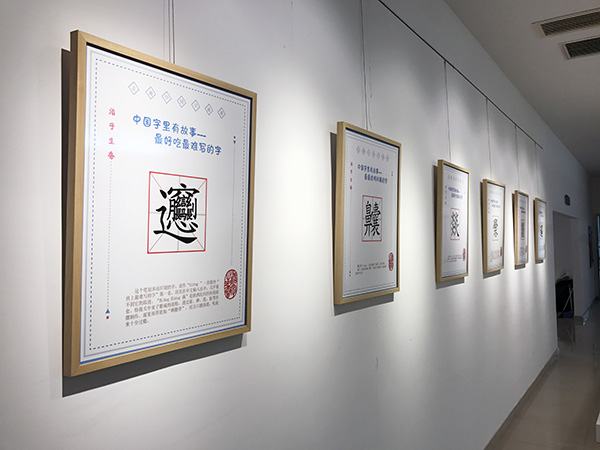
宋体、黑体、楷体等字体如何诞生?看“活字”的前世今生
从远古结绳记事到创世神话中的仓颉造字,至今我们仍然在使用汉字。千年传承让汉字这一神奇的方块字既古老又年轻。从北宋毕昇发明的泥活字,到如今通过电脑实现激光照排技术,黑、宋、仿、楷等字体“告别铅与火、迎来光与电”,成为如今的民族文化遗产。
“活字生香”展现场
澎湃新闻记者从发布会上获悉,“活字生香”活字文化艺术全国巡展将于24日在上海中华印刷博物馆开幕。展览将以“活字”为主题,通过解读活字艺术背后的故事及系列互动,引发公众对濒临失传的中国古老工艺的关注。
据悉,本次展览计划在上海、北京、扬州等地举办巡展,上海印刷技术研究所举办的字体设计大奖赛也将同期举行。
《汉语大字典》用印研所的“宋一体”排版正文,“黑一体”排版标题
通过展览梳理“活字”历史
上海是现代汉字印刷字体创写的发源地,上海印刷技术研究所字体研究室是目前社会上广泛使用的“宋体、黑体、仿宋体、楷体”等汉字印刷字体的原始创写者。2009年,“汉字印刷字体书写技艺”项目被列入上海市非物质文化遗产项目名录。
20世纪60-80年代,印研所创写了宋、黑、仿宋、楷、标宋等十几款字体,原创字稿至今保留。
至今,上海字模一厂仍保留着大量的金属活字。这些活字虽然无法在印刷线上继续“工作”,却代表着汉字印刷字体历史上的重要一环。
“汉字印刷从木刻铅印到电脑印刷是如何演变的?黑、宋、仿、楷四种字体是如何适应我国现代印刷技术的?现代仓颉们是怎样用心血和智慧让印刷字体书写技艺成为民族文化遗产的?从古代走来的活字怎样和当今的生活紧密地结合在一起?” 上海印刷(集团)有限公司副总经理周东介绍,“活字生香”展想要为观众带来的不仅仅是赏心悦目的字体展,更是希望借助这一展览为观众解答“活字”的前世今生、历史渊源。上海这座城市与活字的渊源,也可以在上海站的展览中找到答案,
本次展览将以字模活字艺术传承传播“走出去”为主题,以“活字工艺”为一条主轴,引领整个展览的演绎与发展。共分为8个展馆,分别是:古代活字,近代活字,当代活字,字体之美,古琴谱与活字的对话,活字迷宫与百家姓,活字体验互动,活字艺术衍生品。
观众可以在遍布汉字的墙上寻找属于自己的姓氏。
活字展厅通过活字实物陈列和详细介绍,让观众了解活字从哪里来、为什么需要活字、活字长什么样以及活字经历了哪些发展历程,同时通过活字艺术技艺展示,从刻字、修字、选字、排字、印刷等复杂的工艺步骤,从让观众清晰地了解被称为中国古代“四大发明”之一的活字印刷术。在活字之美展厅,各种大小、颜色的笔画悬垂在空中,通过分解的笔画完成对宋、黑、仿、楷的字体展示,表现出不同字体的特点及吸引力。
在展览的互动体验部分,观众们可以自己动手,印制属于自己的印刷作品;活字艺术衍生品区将展示一批基于印刷文化元素的文创产品,使观众们更直观地感受字体之美。
上海字模一厂副厂长刘现云演示拓印铅活字排版的《兰亭序》。
上海是现代汉字印刷字体创写的发源地
早在唐朝,中国就开始使用雕版印刷术,形成了以书法字体为基础的印刷字体。如今我国常用的印刷字体中,楷体已有1000多年历史,宋体有500多年历史,黑体和仿宋体均有100年左右的历史。
新中国成立后,直至1960年印刷字体还在沿用以前的铜模铅字,活字缺损且字形陈旧杂乱。1956年-1959年间,国家连续公布4批简化字,借简体字刻字补换的契机,国内首个印刷字体研究室于1960年8月在上海印刷技术研究所正式成立,组建起国内第一支印刷字体专业设计队伍,分宋体、黑体、仿宋体、楷体等设计工作组,推陈出新,确立统一标准,开始革新印刷字体。
拓印好的油墨《兰亭序》
传统汉字印刷字体设计要经过铅稿、划线、勾描、填墨、描白五道工艺,完全由设计者手工勾勒润色而成。至今,上海印刷技术研究所字体研究室仍保留着当年设计师手工设计书写的宋体、黑体、楷体、仿宋体等原稿总计超过15万字。
这些印刷字体被各领域广泛使用,如仿宋体广泛应用于党政机关文件、各类期刊正文等;宋体一号最先用于1965年版《辞海》正文字体;宋体二号用于1965年横排版《毛泽东选集》正文字体等。
在发布会上,上海字模一厂副厂长刘现云演示了用油墨拓印铅活字排版的《兰亭序》。这些铅字都是上海字模一厂三四十年前的产品。当时,中国的书籍印刷还大都是用这样的铅活字排版印刷。1980年代末,以王选为代表的科学家发明了汉字激光照排技术,中国传统出版业从此“告别铅与火,迎来光与电”。数量巨大的铅活字成了上海字模一厂的宝贵收藏。如今,上海字模一厂每年都在上海书展现场展示活字拓印,与活字相关的印刷体验、文创开发成了厂里的盘活“活字”资源的新方向。
据字体研究室主任胡丹介绍,目前研究室共设计了37种印刷字体,总计40多万字。如今字体研究室里,设计师手写字体的景象不复存在,大家都在电脑上对新创字体悉心修正,“现在只有在设计最初字形的时候还是铅笔打稿,但不会太多,大概几十个字,此后都是用电脑打稿。”
印研所创制的部分字体广泛应用于字典、毛选等读物印刷
研究室还为2019年即将出版的新版《辞海》重新设计了宋体、黑体、网络版字体三套新字体,共计9万字。胡丹表示,展览开幕式上将举行电子辞海的字体首发仪式,希望以此引起公众对知识产权保护的关注。
“活字和印刷密不可分,作为新时代的上海印刷人,必须将‘活字’这一历久弥新的民族文化遗产好好传承发扬,通过创新,赋予活字新的生命力。” 周东说。